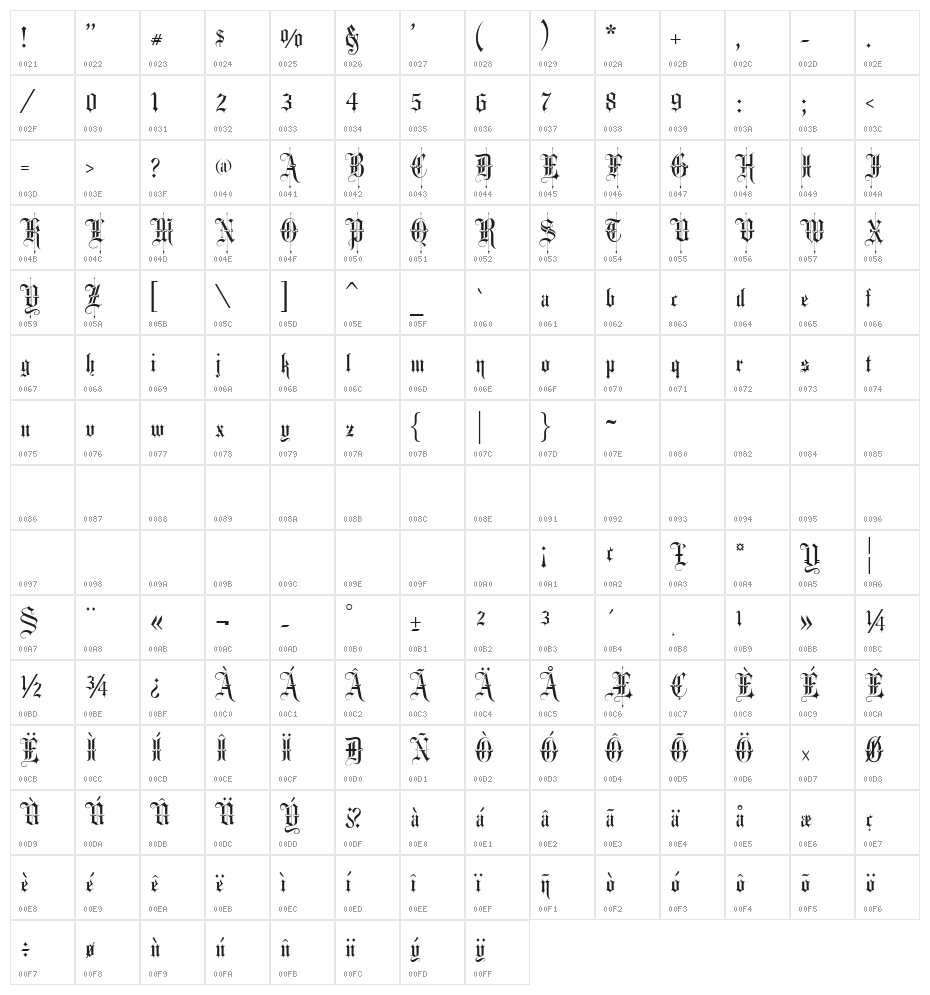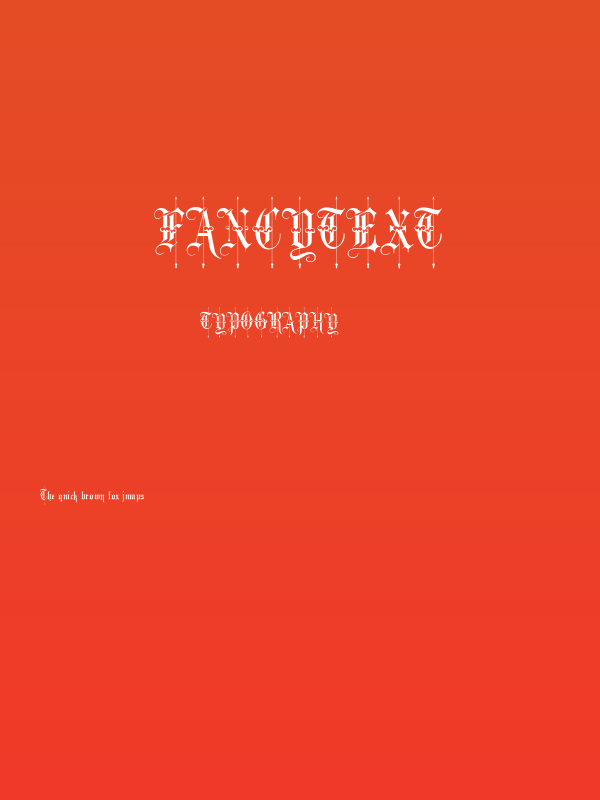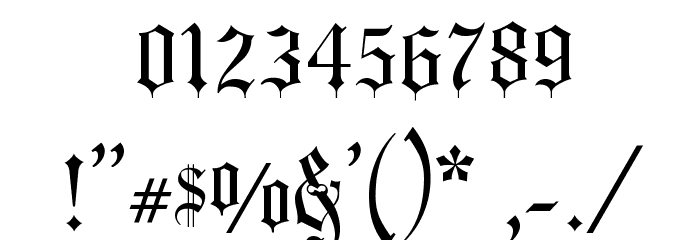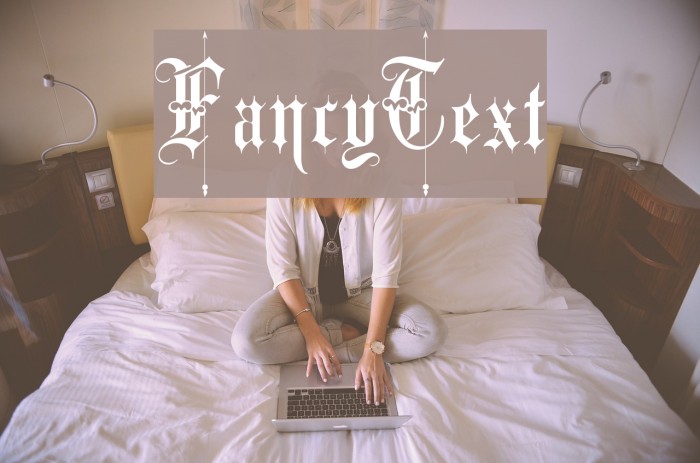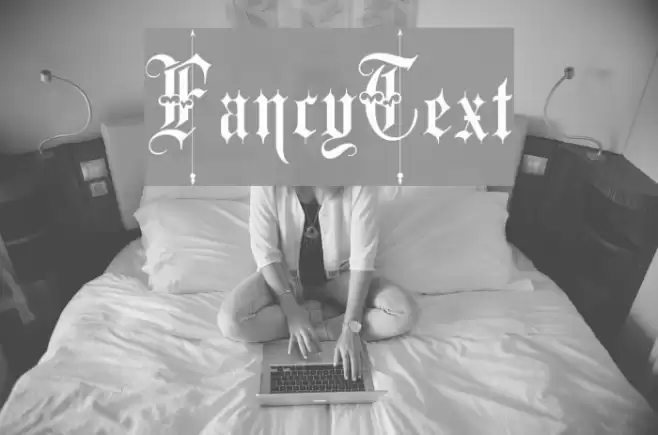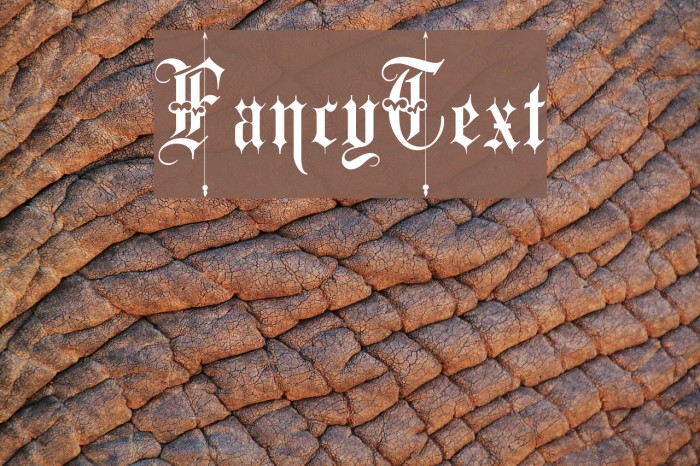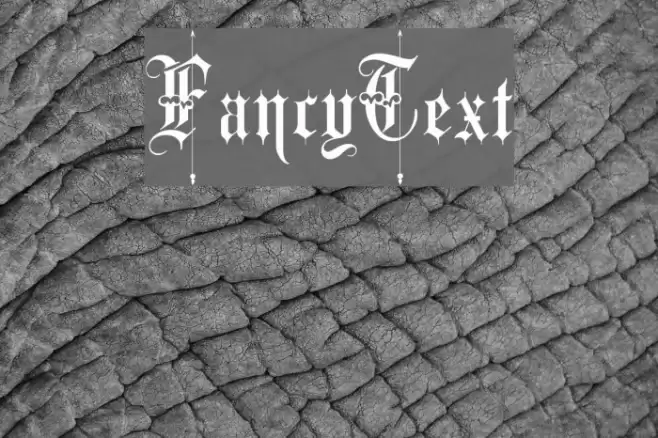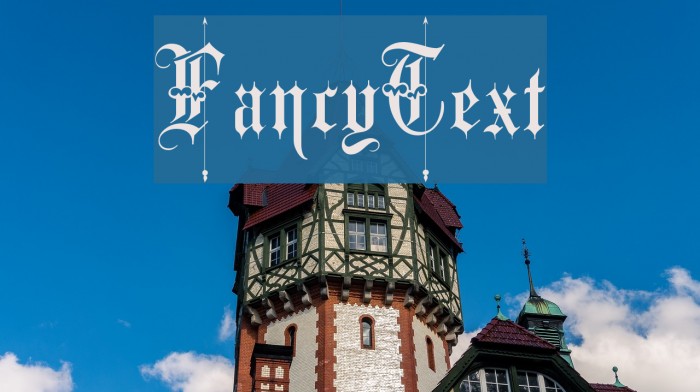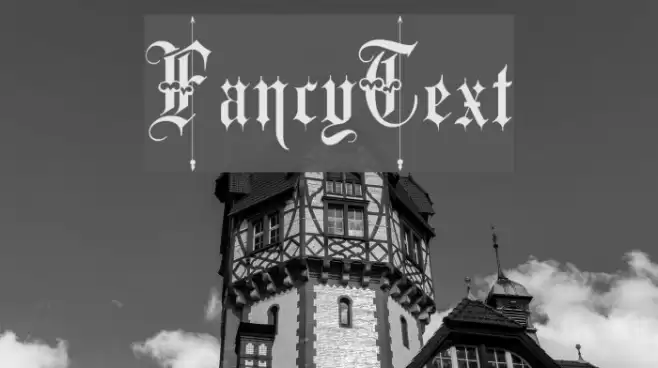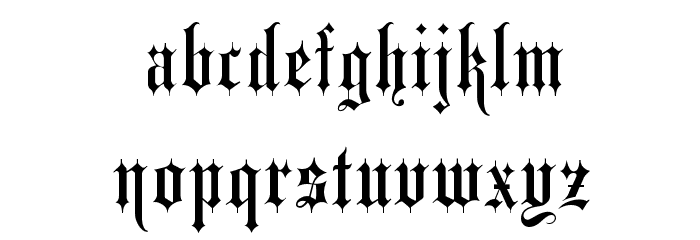
FancyText Font
✎ Gothic
| Kategorien | Gothic |
| Gesamtstil | Vintage |
| Vorgeschlagene Projekte | Ideal for projects requiring a historical or Gothic touch, such as book covers, posters, or branding for vintage-themed events. |